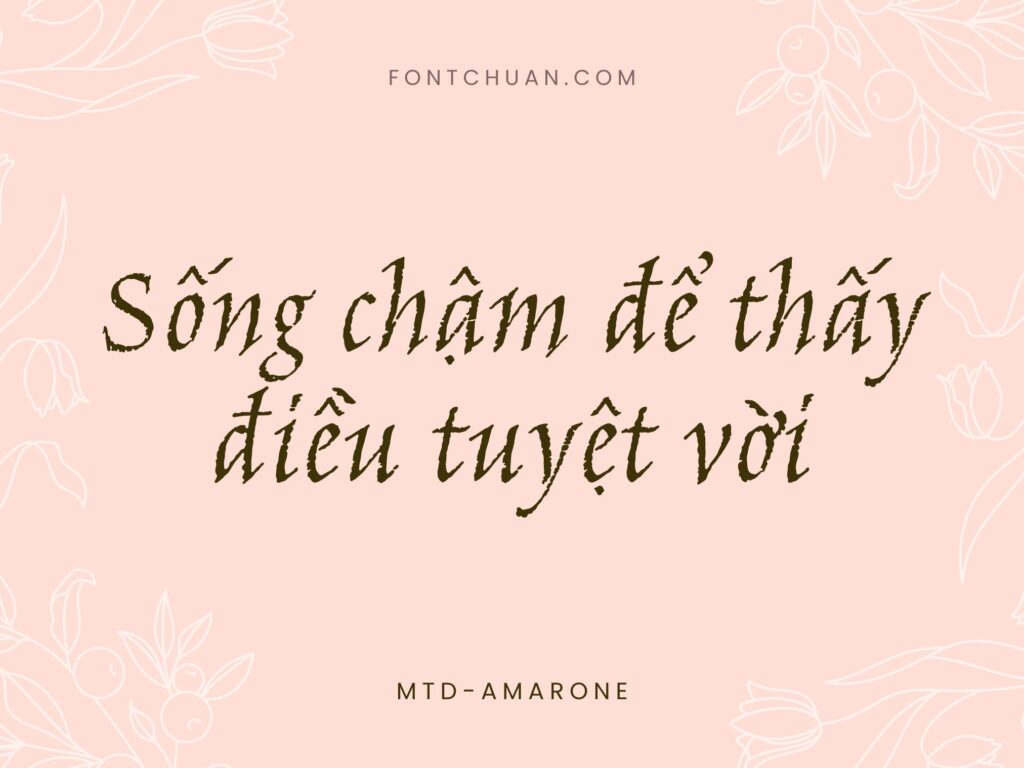
Font Amarone là một kiểu chữ serif thanh lịch, được thiết kế bởi Phuong Nguyen và phát hành trên nền tảng FontStruct. Lấy cảm hứng từ hình dáng của ly rượu vang và giọt rượu, Amarone mang đến sự kết hợp giữa phong cách cổ điển và hiện đại, tạo nên sự độc đáo cho các thiết kế.
Phiên bản Amarone đã được Việt hóa bởi Mộc Hạ, hỗ trợ đầy đủ tiếng Việt cùng hơn 130 ngôn ngữ khác, mở rộng khả năng ứng dụng trong thiết kế đa ngôn ngữ. Font này đã được thành viên Font Chuẩn sưu tầm và chia sẻ, đáp ứng nhu cầu của cộng đồng thiết kế. Với thiết kế bao gồm các ký tự serif tinh tế và các đường nét trang trí độc đáo, Amarone phù hợp cho các ứng dụng như thiết kế logo, tiêu đề, bao bì sản phẩm và các ấn phẩm quảng cáo. Các ngành nghề như quảng cáo, giáo dục, công nghệ và ẩm thực có thể tận dụng font này để tạo ra thiết kế ấn tượng và thu hút.